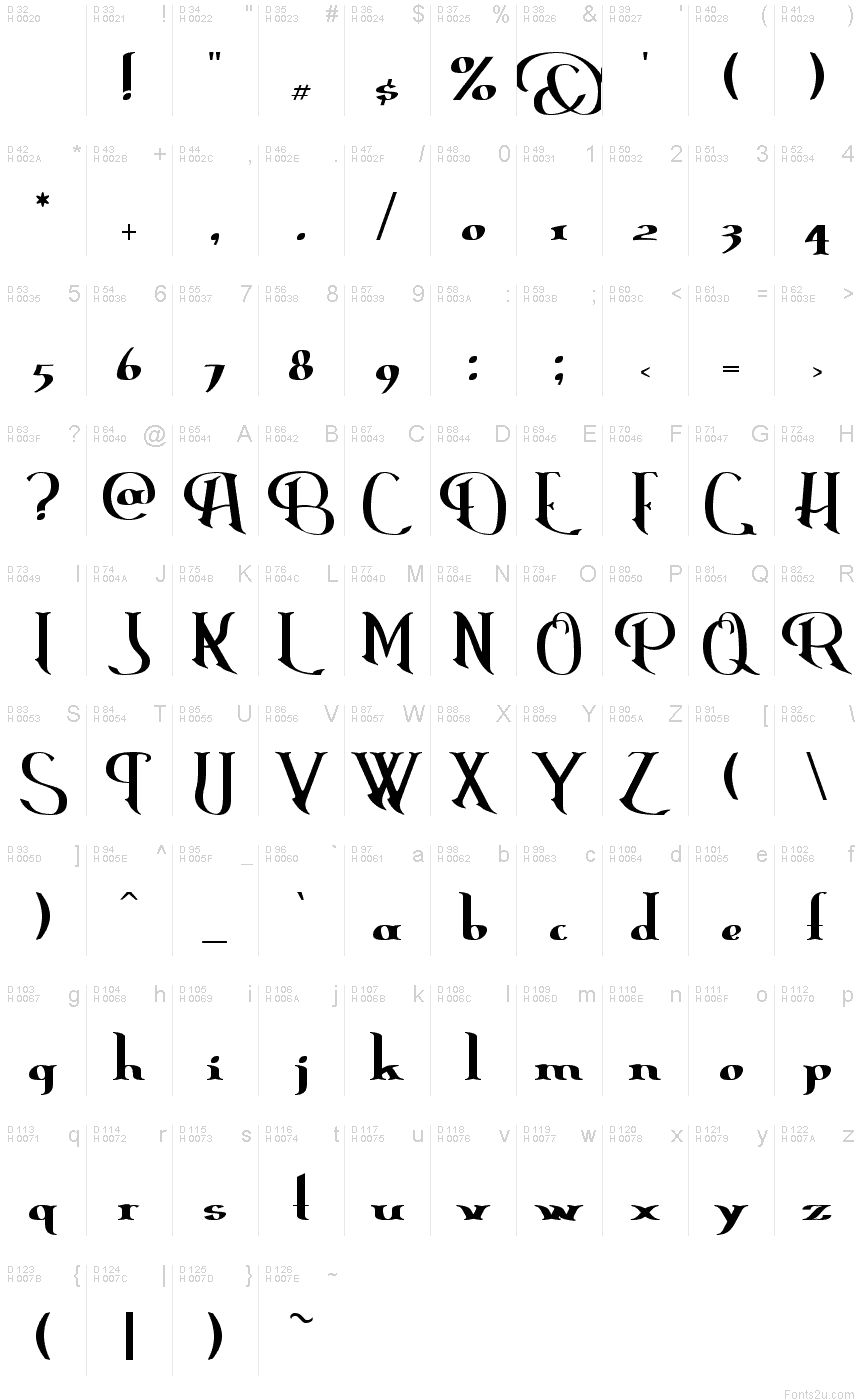
Erasmus od PJL to darmowy krój gotycki, który nadaje słowom atramentowy, średniowieczny klimat. Wysokie, przypominające ostrza litery początkowe oraz masywne, zaokrąglone znaki tworzą nastrój jednocześnie uroczysty i nieco groźny – jakby pismo wyjęto prosto ze starego grymuaru. Pociągnięcia sprawiają wrażenie wyrytych, a nie narysowanych, co nadaje nagłówkom namacalny, kamienny charakter, który natychmiast przyciąga wzrok.
Erasmus w dużych rozmiarach idealnie sprawdzi się na wciągających okładkach książek, w tytułach gier fantasy lub horrorów, logotypach zespołów, plakatach tematycznych, brandingu w stylu tatuażu czy klimatycznych opakowaniach. Ten darmowy font świetnie współgra z prostym krojem bezszeryfowym w tekście uzupełniającym, pozwalając Erasmusowi przejąć główną rolę w nazwach, tytułach i kluczowych hasłach.